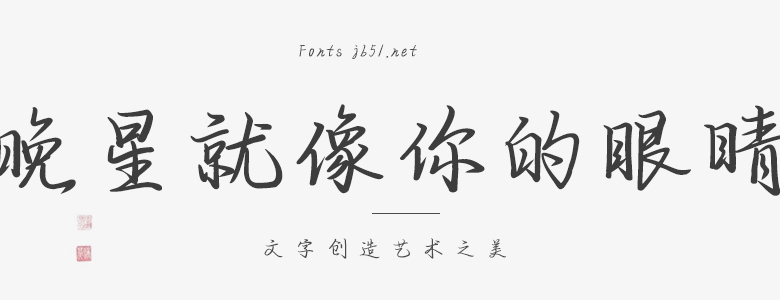
晚星字体,如同其名字一般,仿佛是夜空中闪烁的星星,宁静而神秘。它的设计理念源自于我对夜晚星空的深深热爱。每一笔、每一划都好像是一颗星星,串联起我与宇宙之间的深厚情感。 晚星字体的笔画线条流畅,犹如流星划过夜空,带有一种流动的美感。字体的粗细对比,使每个字母都充满了动感和生命力。就像星星在夜空中穿梭,无论是明亮还是暗淡,都是构成美丽夜景的必要元素。 晚星字体的设计细节丰富,且富有艺术性。像眼睛一样的独特设计元素,使得这款字体在众多设计中脱颖而出。每个字母都有一个独特的“眼睛”形状,仿佛这些字母都是有生命的,正在用他们独特的眼神和你交流。 这款字体的使用场景广泛,无论是正式的商业场合,还是富有创意的设计作品,晚星都能在其中扮演重要的角色。它不仅是我对星空的热爱,更是我对设计的执着和热忱的体现。 晚星字体,就像我的眼睛,它不仅看到了我与星星的约定,也看到了我对设计的热爱和执着。我希望你能通过使用这款字体,感受到我对设计的热情和对生活的热爱。